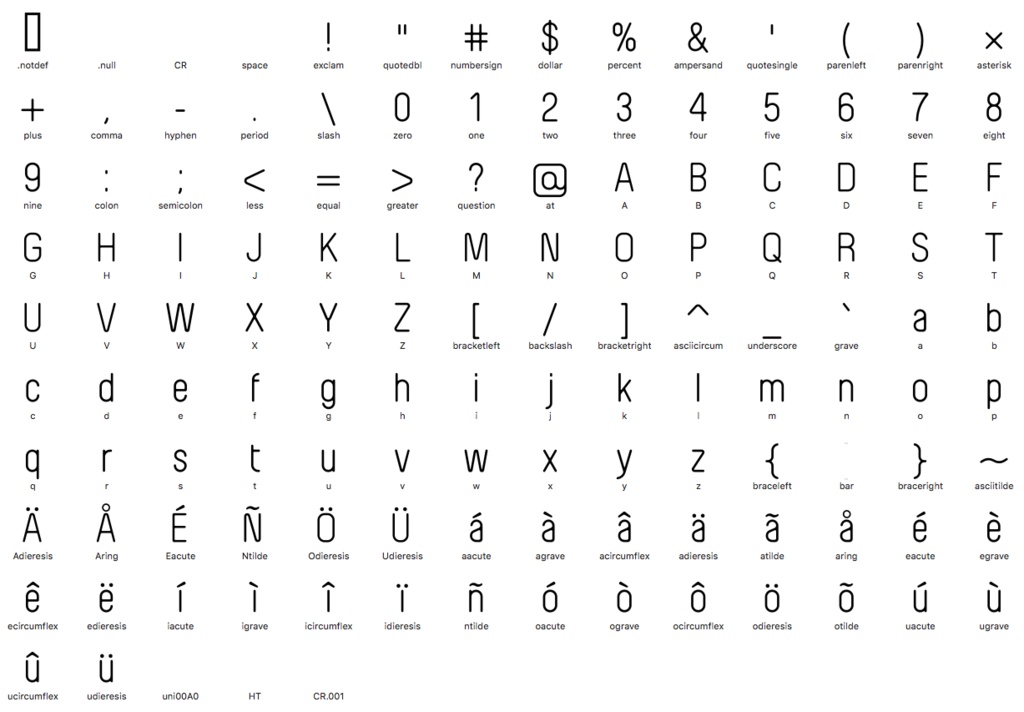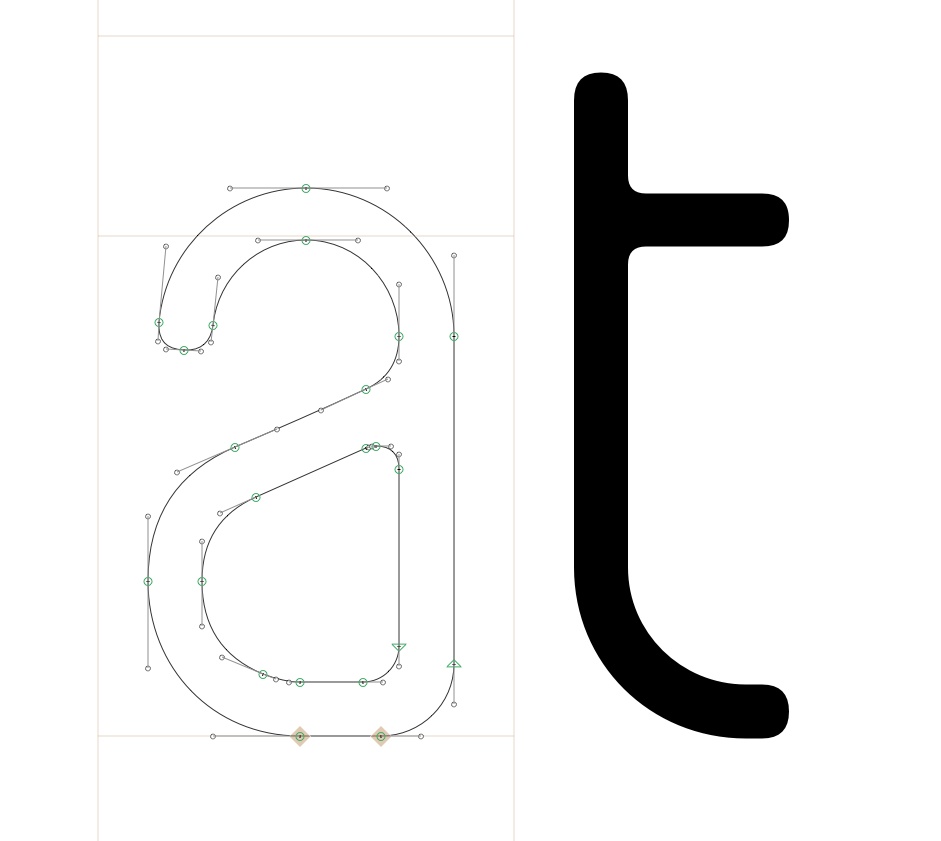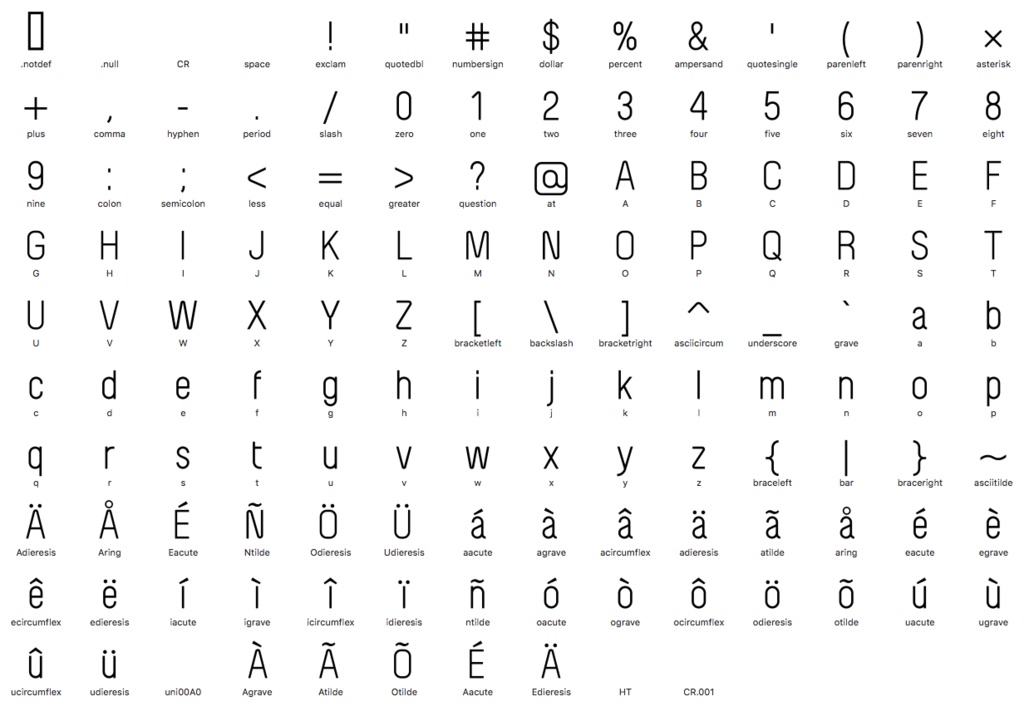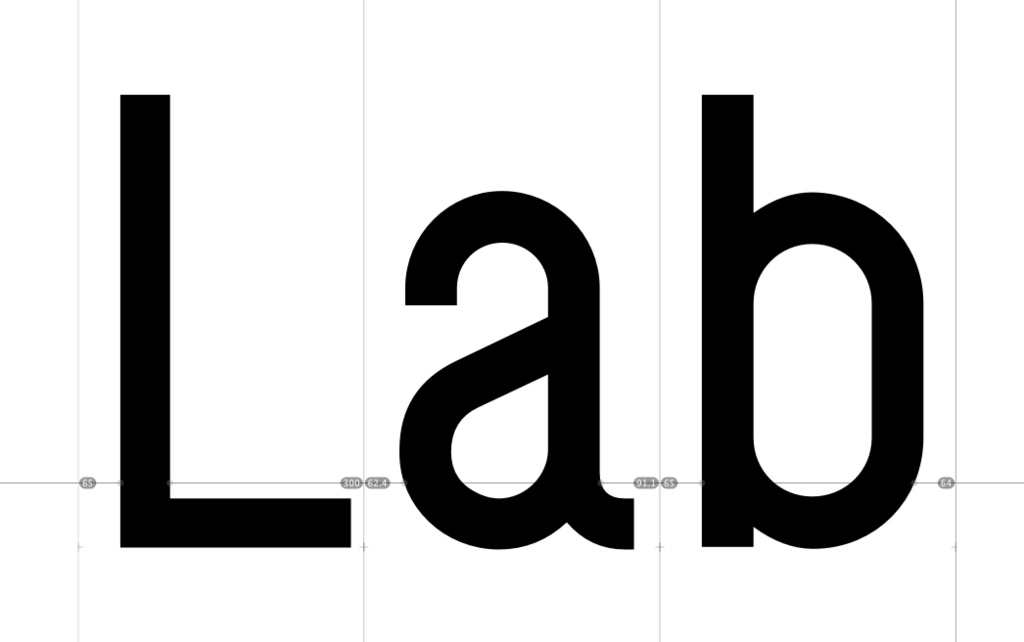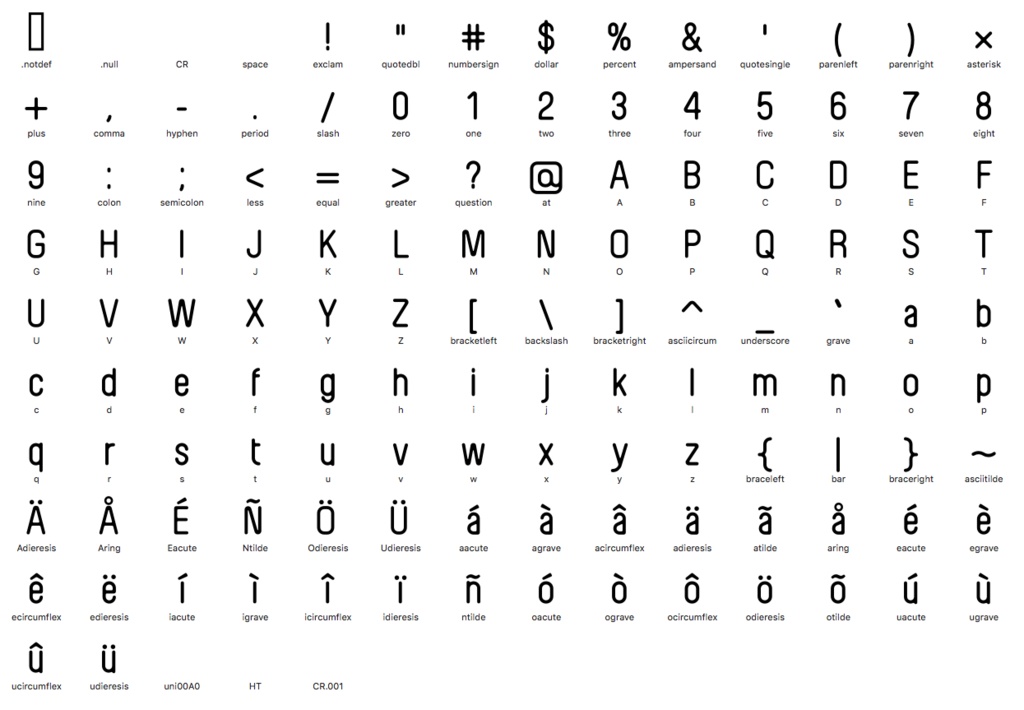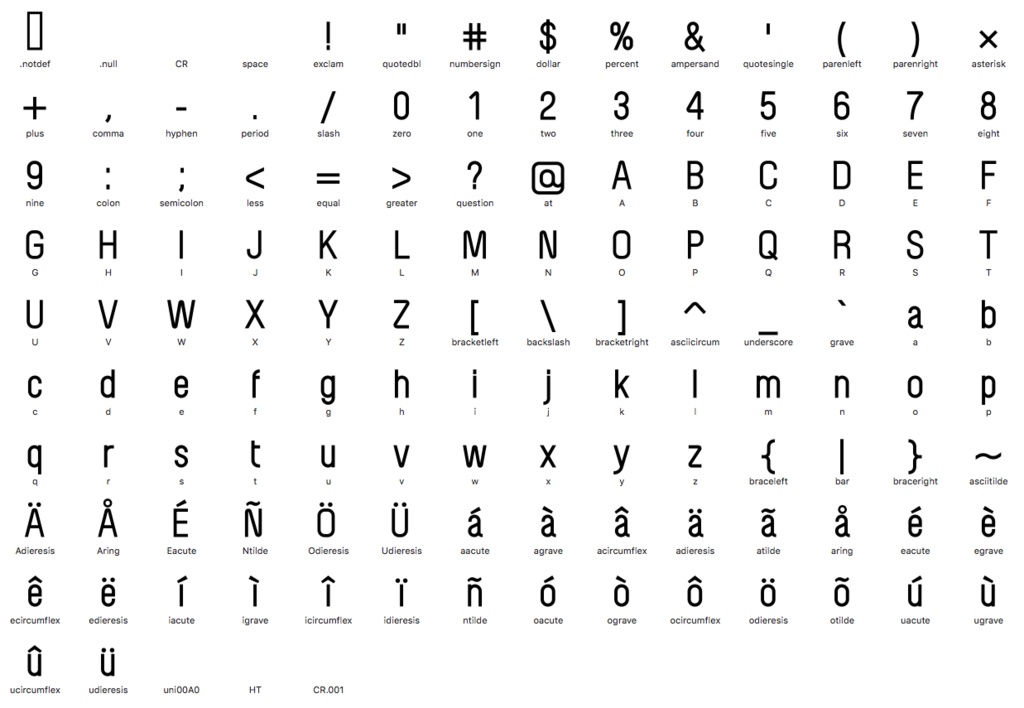
LabLifeフォント
LabLifeフォントは、モダンな欧文フォント。均一な太さが現代的で、未来を感じさせるロゴタイプに向いています。シャープなデザインと、少しかわいい雰囲気が個性的です。 普通の太さのレギュラーと、太めのボールドを収録。また角丸を取ったラウンドレギュラーとラウンドボールドも収録。合計4フォントになります。 動作環境 Mac:システム/OS X対応(10.x)〜最新のOS X Windows:OS/日本語版Windows2000、XP、VISTA、Windows7〜11以降 フォント形式:OpenTypeフォント 収録文字数について アルファベットのみの書体になります。 安心して使えるロイヤリティフリーの書体 あらゆる商用・デザイン用途(印刷物・ゲーム・アプリ・映像・動画・ロゴ・同人作品)に使用できる、商用申請の必要のないロイヤリティフリーの書体になります。文字の加工・変形も可能です。ご安心ください。 安心して使える商用利用可のオリジナルフォントです。 1商品(1ライセンス)につき1ユーザー1PCのみがご利用いただけます。複数人で使用する場合は人数分をご購入ください。